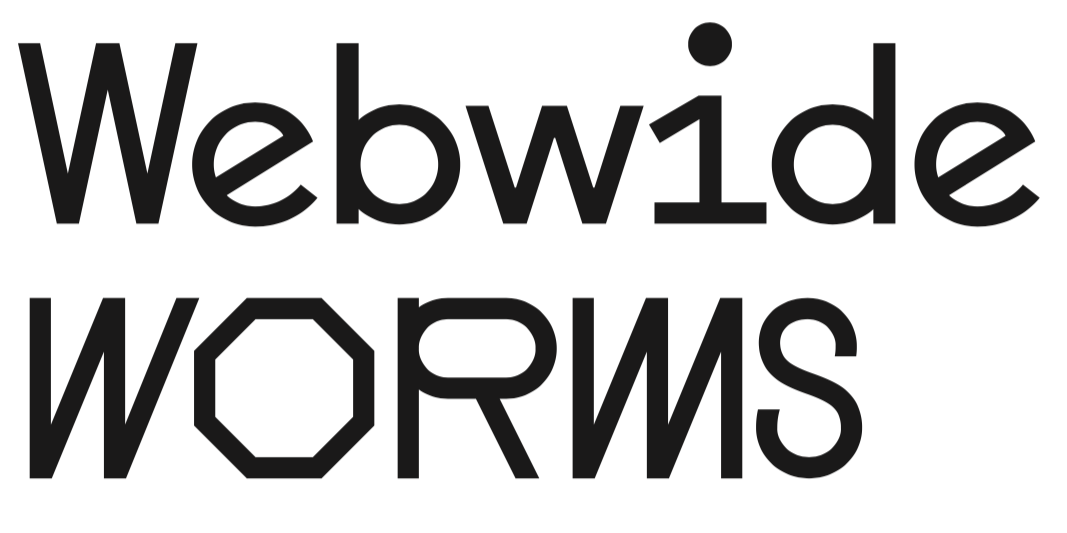
Heal The Web - Free font
Ich schätze das dieser Font bei den meisten echten Typographen schlimme Kopfschmerzen verursachen könnte. Trotzdem würde ich mich über Feedback freuen.
Momentan spiele ich mit dem Gedanken noch ein Ultrafettes Master zu machen und daraus einen variablen Font zu generieren. Es stellt sich natürlich ein bisschen die Frage ob das da draußen irgend jemanden interessiert oder man das Ganze als abgeschlossenes Experiment abhaken sollte.
Ich finde die Fonts irgendwie amüsant. Sie wecken grad im Fließtext Erinnerungen bei mir an diese Pixelfonts, die damals extra für Flash-Anwendungen genutzt/entwickelt wurden.
Ich kann mir nicht vorstellen, die irgendwann einzusetzen, aber die Idee ist nett und die Fonts umfangreich.